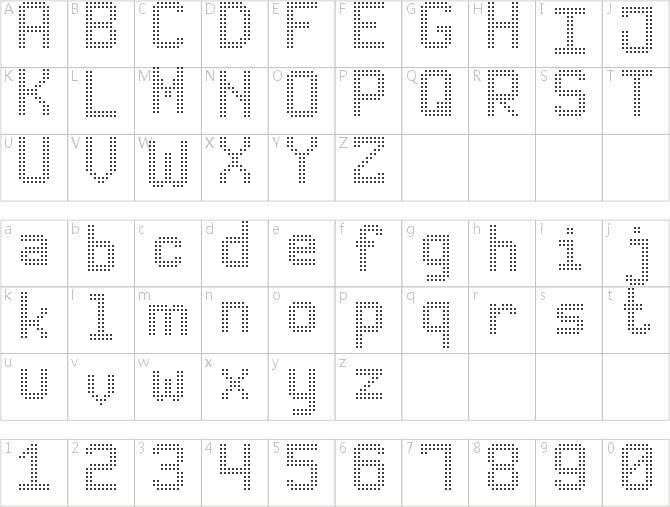
advanced_dot_digital7 詳情頁
advanced_dot_digital7字體字庫是一款讓人賞心悅目、百看不厭的英文字體,適合各類廣告和產(chǎn)品包裝設(shè)計應(yīng)用,字體大小0.17MB,格式為ttf字體,上傳用戶是M_墨董,作者/版權(quán)方為未知